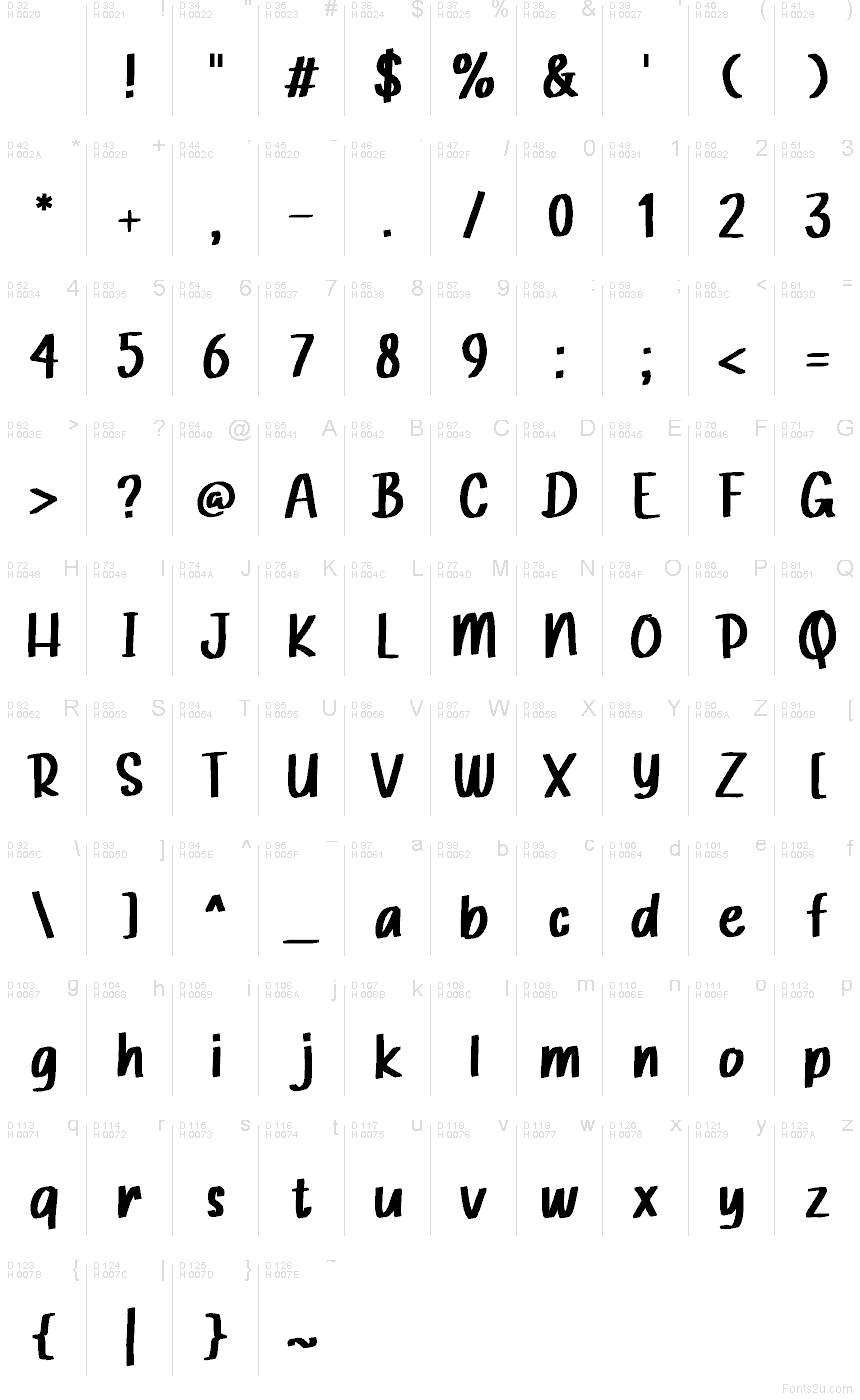
Potato Gatcha
Potato Gatcha від Hello Good Studio - це безкоштовний рукописний шрифт із невимушеним, злегка нерівним накресленням, яке надає літерам ритміки ручного письма. Форми виглядають заокругленими, але не ідеально гладкими, а легкі нахили та шорсткі краї не дають дизайну виглядати механічно.
Potato Gatcha чудово підходить для пакування, меню кав'ярень, заголовків блогів, дописів у соцмережах та дитячих проєктів, оскільки зберігає дружній рукописний тон, не перевантажуючи дизайн. Цей безкоштовний шрифт також добре пасує для коротких цитат, листівок та неформального брендингу, коли вам потрібне відчуття ручного скетчу, а не ідеально вивіреної графіки.